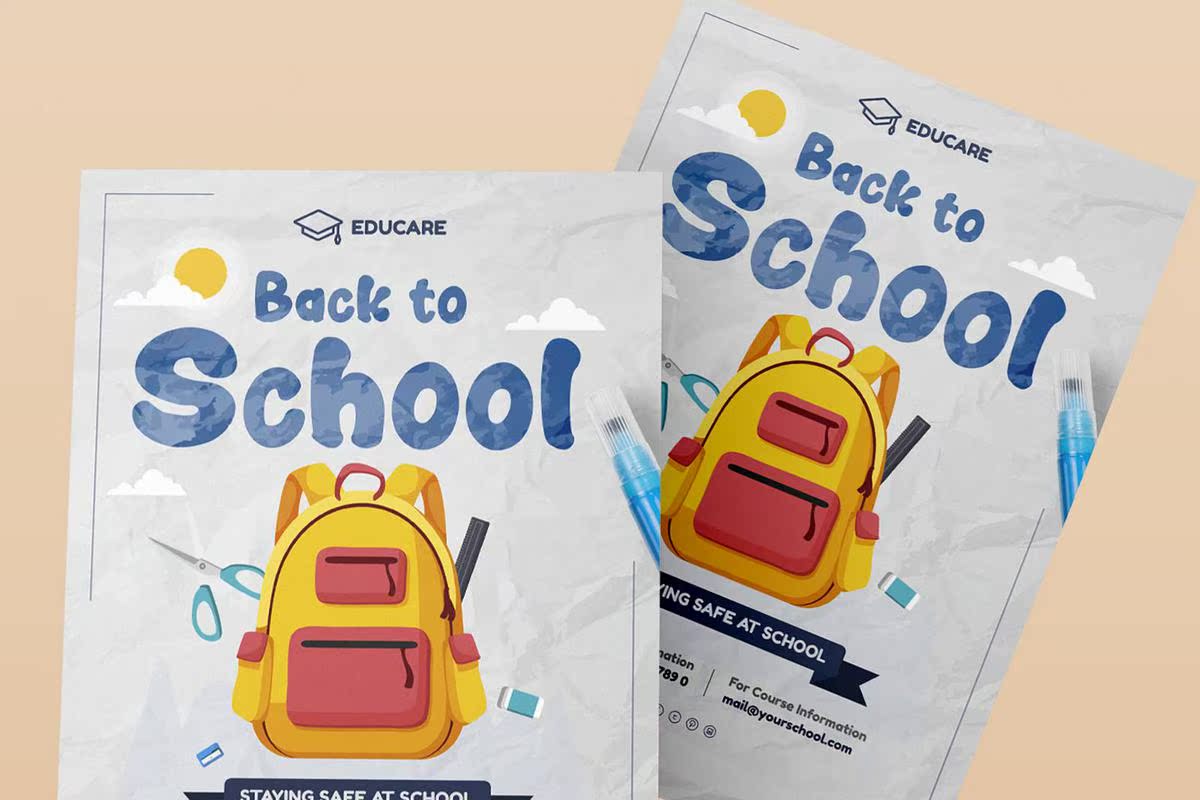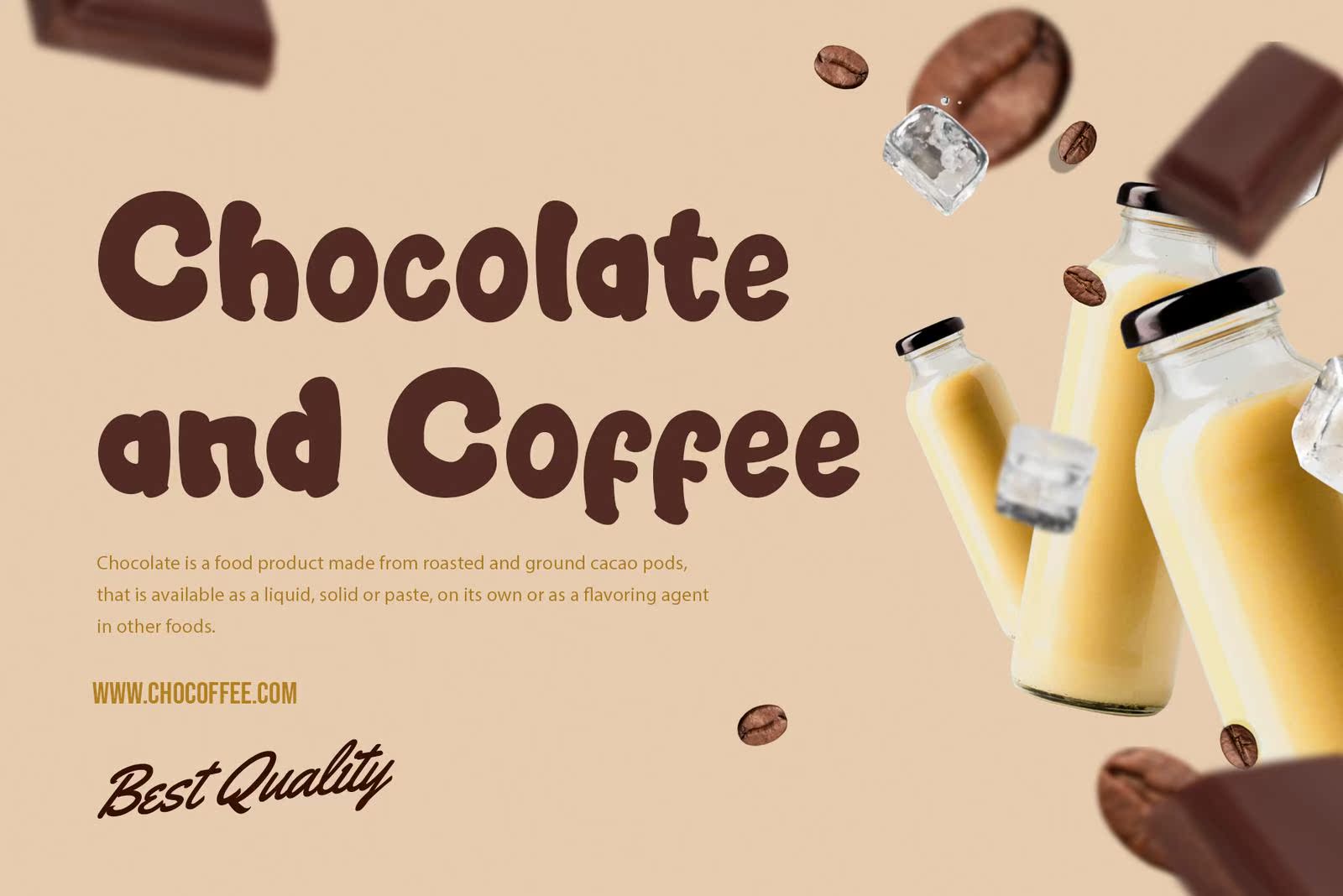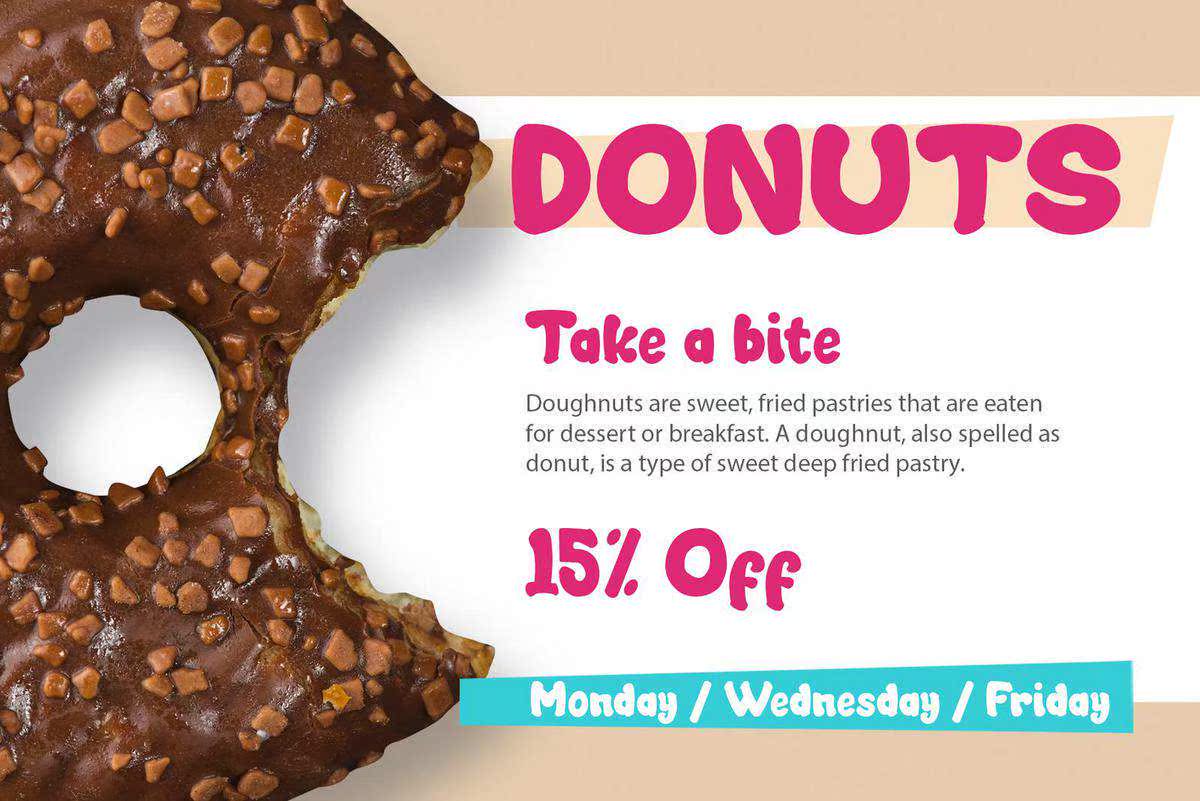
简介新版本,MoccasweetDisplayType字体。此字体集适用于品牌徽标、邀请、问候卡或任何类型的项目。此字体集具有多语言功能和样式变化,将进一步增强您作品的外观。简介新版本,MoccasweetDisplayType字体。此字体集适用于品牌徽标、邀请、问候卡,即使是任何类型的项目。具有多种语言功能和样式变化,这种字体将进一步增强您的工作的外观。